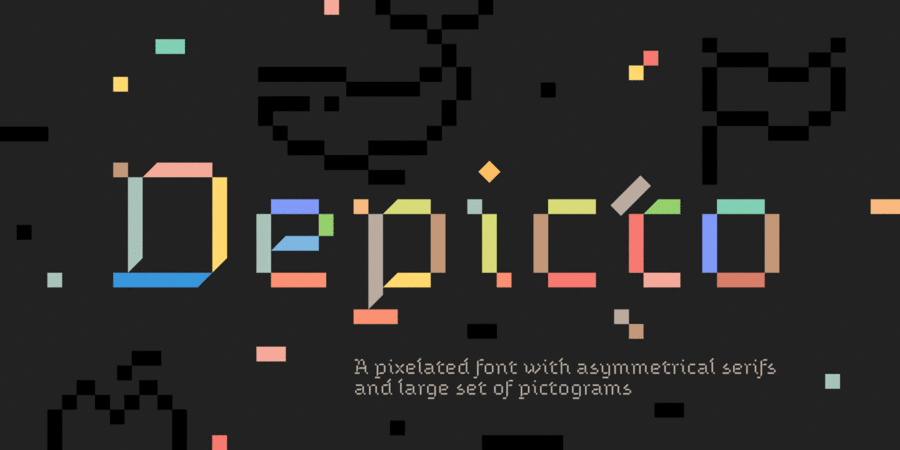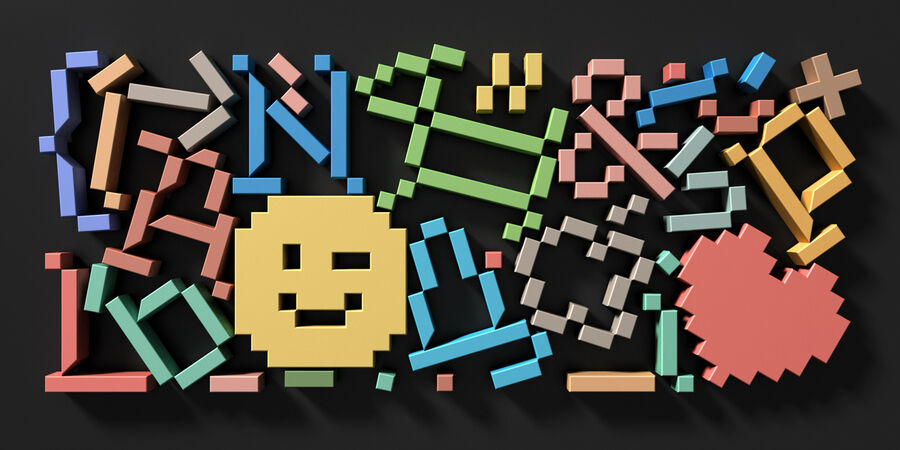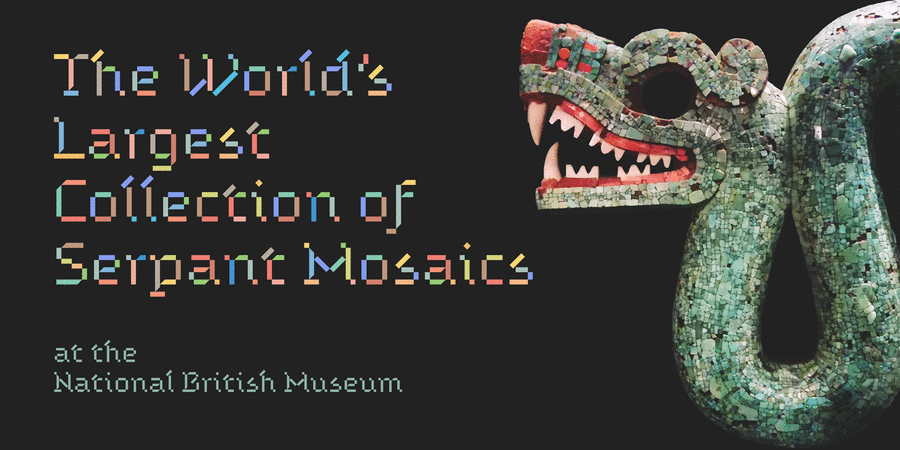
Depicto — це піксельний шрифт із асиметричними засічками, що зображує емодзі у грубих мозаїчних формах і представлений двома стилями, які чудово доповнюють один одне — Mono (звичайний шрифт) і Mosaic (кольоровий шрифт). Основною особливістю шрифту є великий набір піктограм, які активуються за допомогою стилістичного набору 1 та друкуються прямо в тексті за допомогою ключових слів на кшталт :smile: :happy: :sad: :pear: :rose: :horse: :bike: :house: тощо. Дивіться повний перелік більш ніж 600 піктограм в Specimen pdf.
Концепт У дитинстві я любив грати пластиковим конструктором. І звичайно ж, мені подобалися 8-бітні відеоігри. Все це знайшло відображення в шрифті Depicto. З огляду на 8-бітність майже всі розміри кратні 8 – елементи літер мають ширину 80 пунктів і довжину 80, 160, 240, 400 тощо, так само як і відстань між літерами та вертикальні метрики. Хоча й натхненний пікселізацією, шрифт все ж грає з власною геометрією. Використовуючи прості квадратні форми, він балансує між піксельною сіткою та діагональною мозаїкою. Побудова літер заснована на прямокутниках – горизонтальних, вертикальних і повернених на 45 градусів. Важливо відзначити, що літери складаються з окремих непересічних елементів, кожен з яких у стилі Depicto Mosaic пофарбований у різні кольори. Шрифт також використовує верхні ліві та нижні праві горизонтальні засічкові штрихи. Такі асиметричні засічки характерні для української типографії ще з часів Георгія Нарбута. Їх діджиталізація та пікселізація дозволяє побачити художні константи під новим кутом. Технічні деталі Specimen: https://michaelrafailyk.com/typeface/specimen/Depicto.pdf Функція Кольорові шрифти Mosaic COLOR (для веб браузерів та Windows програм) та Mosaic SVG (для програм Adobe) присвячений моїй любові до кольорового пластикового конструктору. Кожен елемент літери забарвлений у випадковий, але неповторюваний колір із палітри з 17 попередньо визначених кольорів. Ця палітра підібрана таким чином, щоб вона виглядала досить контрастно як на білому, так і на чорному тлі. Але, звичайно, ви можете змінити палітру в Photoshop, використовуючи Color Overlay в Blending Options (див. приклади на останніх промо зображеннях), або в Illustrator, перетворивши текст на контури, а потім Recolor Arkwork. Кольорові шрифти підтримуються починаючи з: Photoshop CC 2017, Illustrator CC 2018, InDesign CC 2019, QuarkXPress 2018, Pixelmator (macOS 10.14), Sketch (macOS 10.14), Affinity Designer (macOS 10.14), Paint.NET (Windows 10), Microsoft Word (Windows 10), Windows 10, macOS 10.13 High Sierra, Safari 11 (macOS 10.13, iOS 12), Chrome 70, Firefox 26, Opera 58, Edge 12 (Windows 10), IE 9 (Windows 8). Додатки, які ще не підтримують кольорові шрифти: Figma, Adobe XD, Premiere Pro, After Effects. В цих програмах, стиль шрифту Depicto Mosaic буде відображатись стандартним чорним кольором. Stylistic Set 1 “Pictograms”: Основна особливість шрифту — великий набір із понад 600 піктограм і смайлів. Дивіться повний перелік піктограм і їхніх ключових слів у пдф-файлі Specimen. Цей набір не охоплює всі можливі піктограми юнікоду, але включає найбільш популярні, і набір може бути розширено в майбутніх оновленнях шрифту. Є три способи використання піктограм. Як застосувати стилістичний набір. InDesign (2017+): Character panel > OpenType button > Stylistic Sets. Stylistic Set 2 “Change Emoji Skin Tone”: Таким чином можна змінити відтінок шкіри смайликів. У стилі Depicto Mosaic класичні жовті смайли стають коричневими. А в стилі Depicto Mono результат залежить від кольору фону – для білого фону білі обличчя замінюються чорними, і, відповідно, для чорного фону чорні обличчя замінюються білими. Пам’ятайте: коли змінюєте колір фону зі світлого на темний або навпаки (використовуючи шрифт Depicto Mono), обличчя виглядають інвертованими, і ви можете застосувати цей стилістичний набір, щоб ре-інвертувати кольори назад. Stylistic Set 3 “Arrows”: Left <- Right ->; Up <| Down |> Left Right <-> Up Down <|> North West <\ North East /> South East \> South West Шрифт розробив Михайло Рафайлик у 2023 році та оновив і розширив мовну підтримку в 2024. Світ ловив мене, та не спіймав!
Асоціації з сімейством шрифтів DepictoОсобистість і характер гарнітури:
ефектний, якісний, культурний, благородний, красивий, майстерний, естетичний, художній, дорогоцінний, оригінальний, виразний, характерний, динамічний, історичний, унікальний, цікавий, гуманітарний, різкий, дивний, старовинний, старомодний, фантастичний, сакральний, релігійний, церковний, кам'яний, твердий, незвичайний, артистичний, архітектурний, експериментальний, самобутній, ролевий, творчий, колоритний, середньовічний, освічений, ламаний, ремісничий, комп'ютерний, гострий, чіткий, грайливий, казковий, ігровий, ритмічний, яскравий, потішний, прикольний, дробный, екзотичний